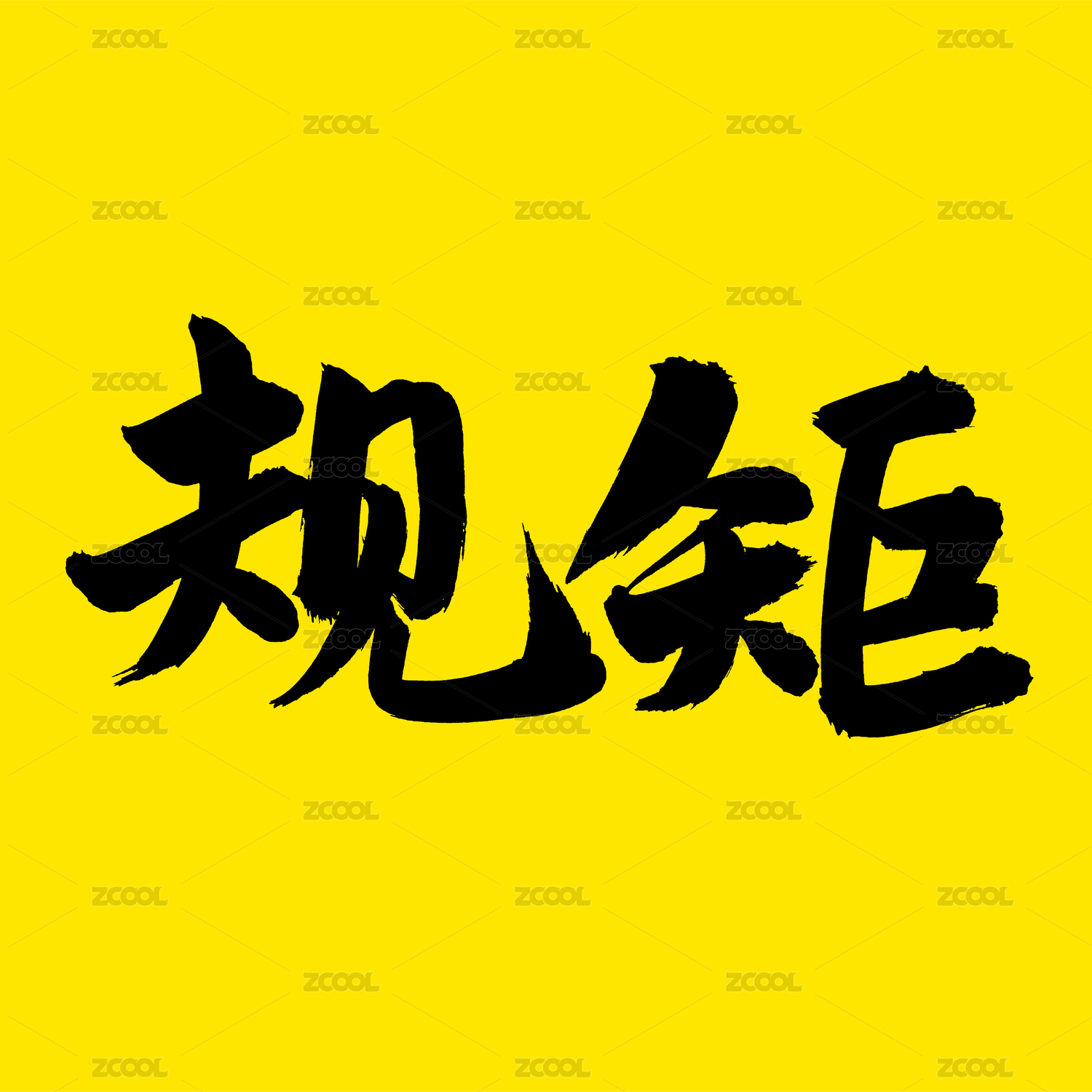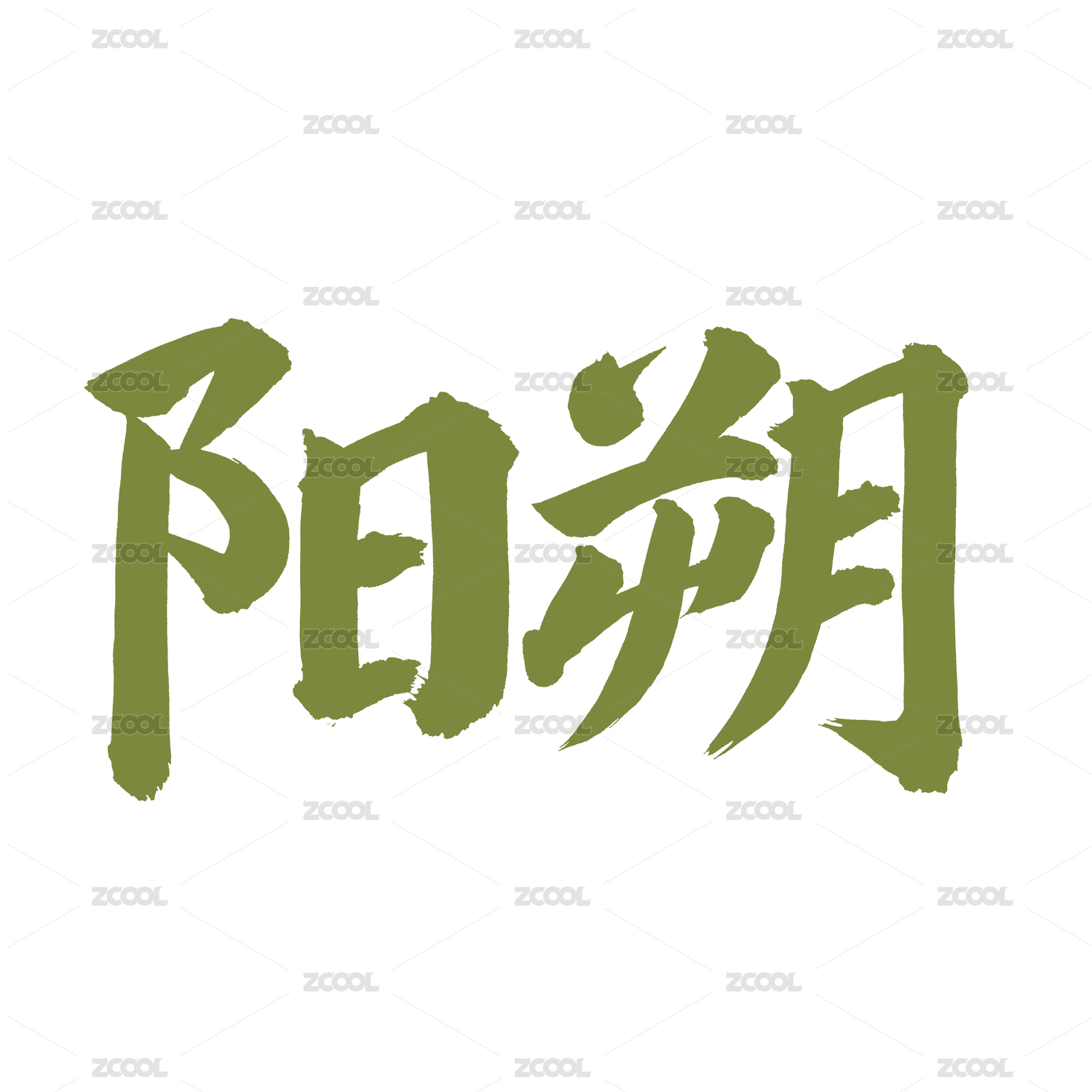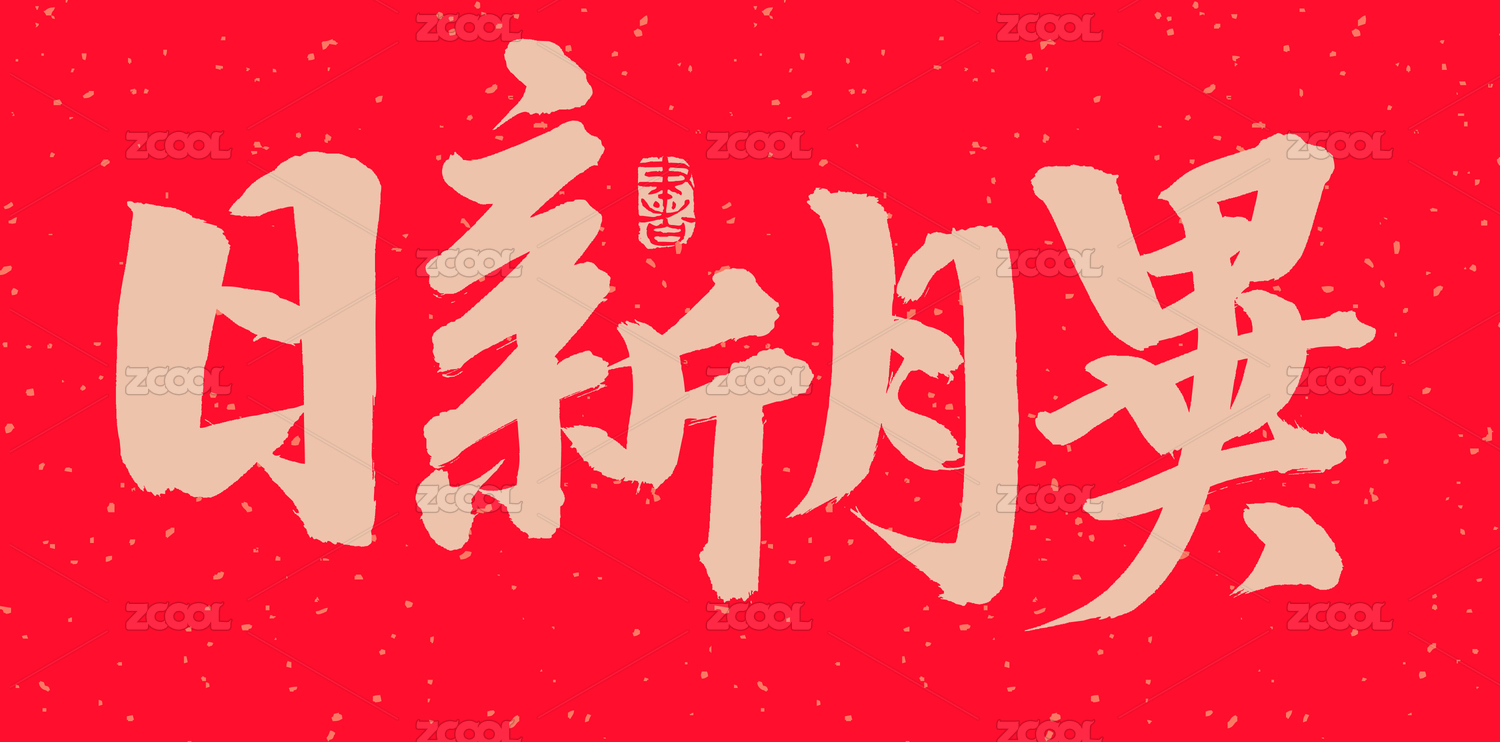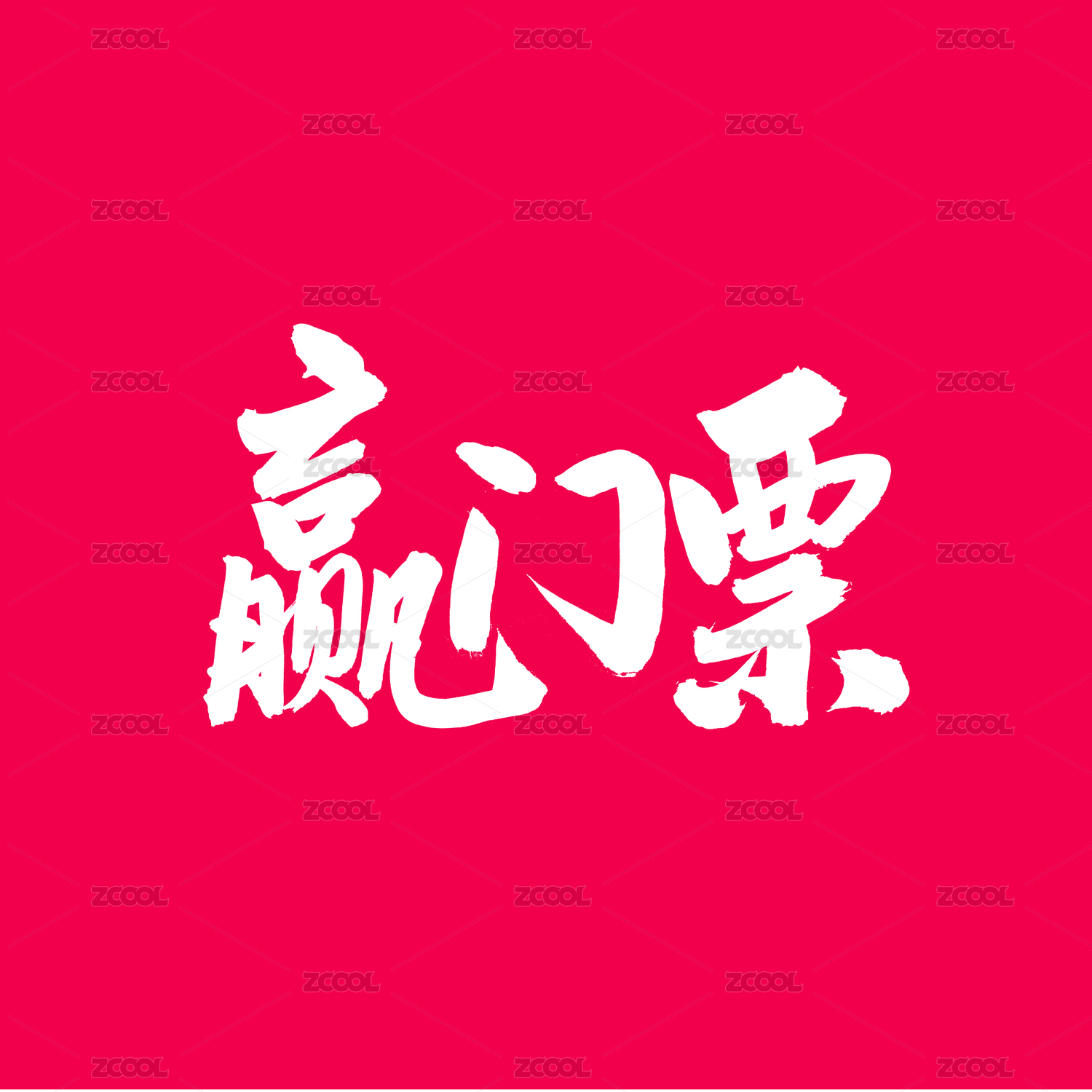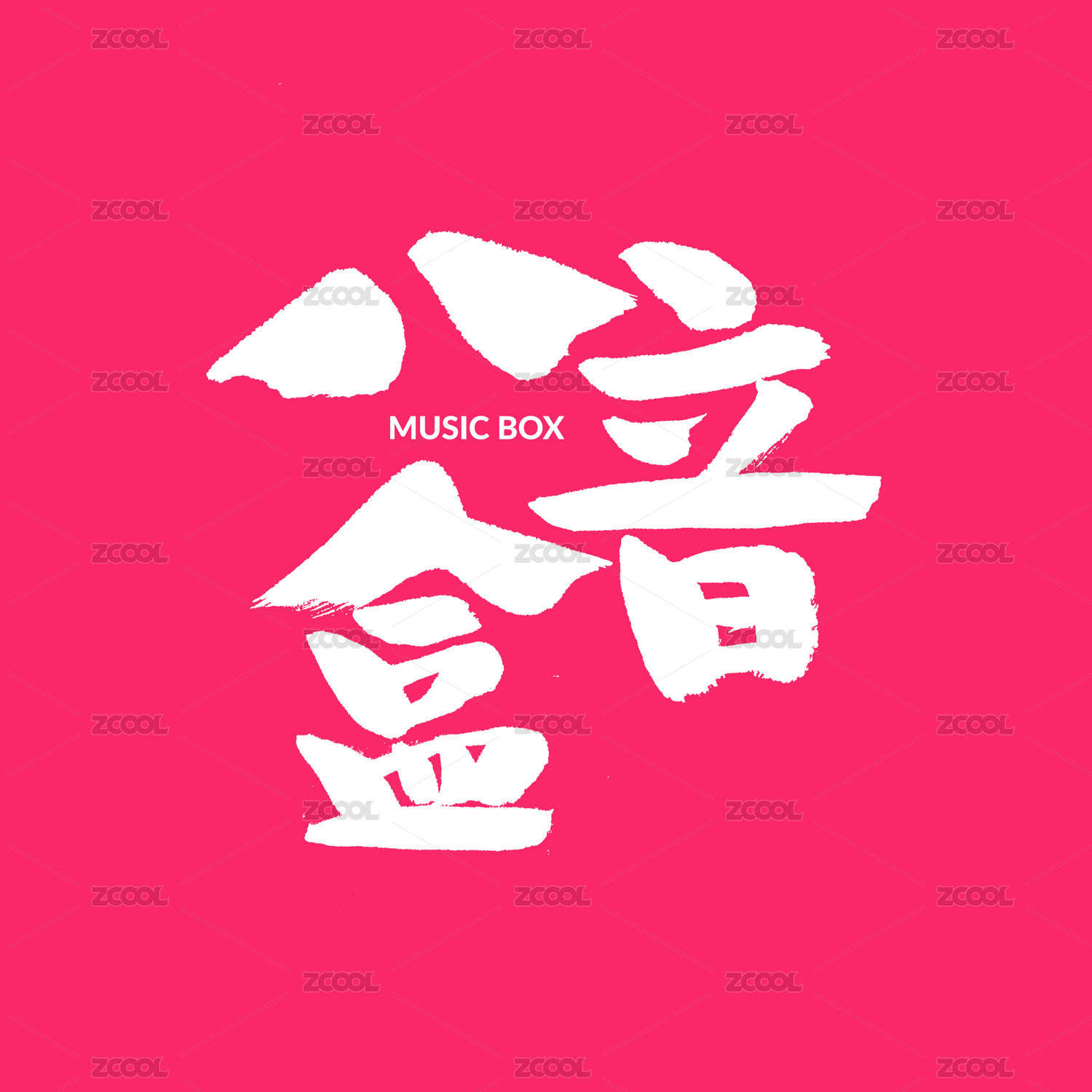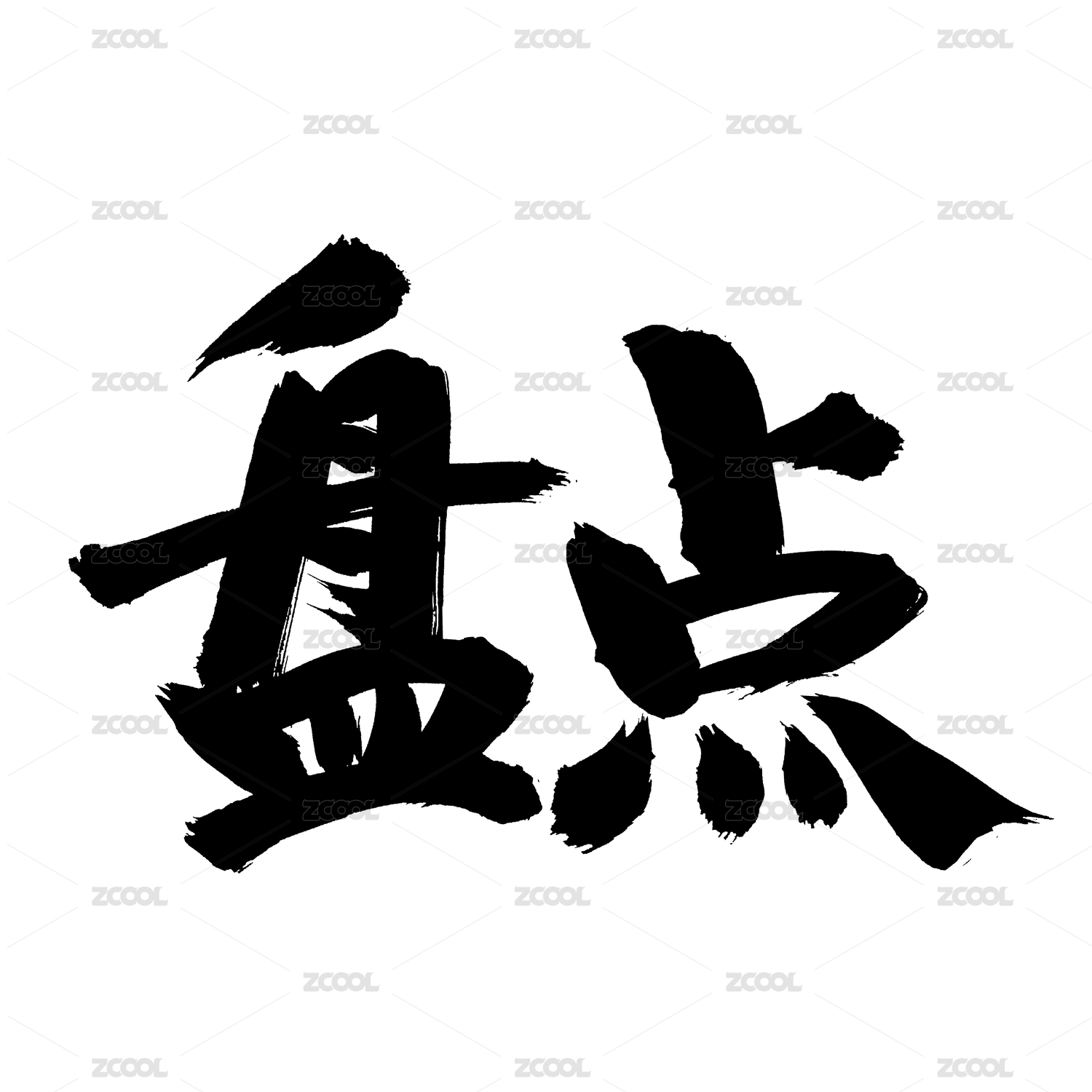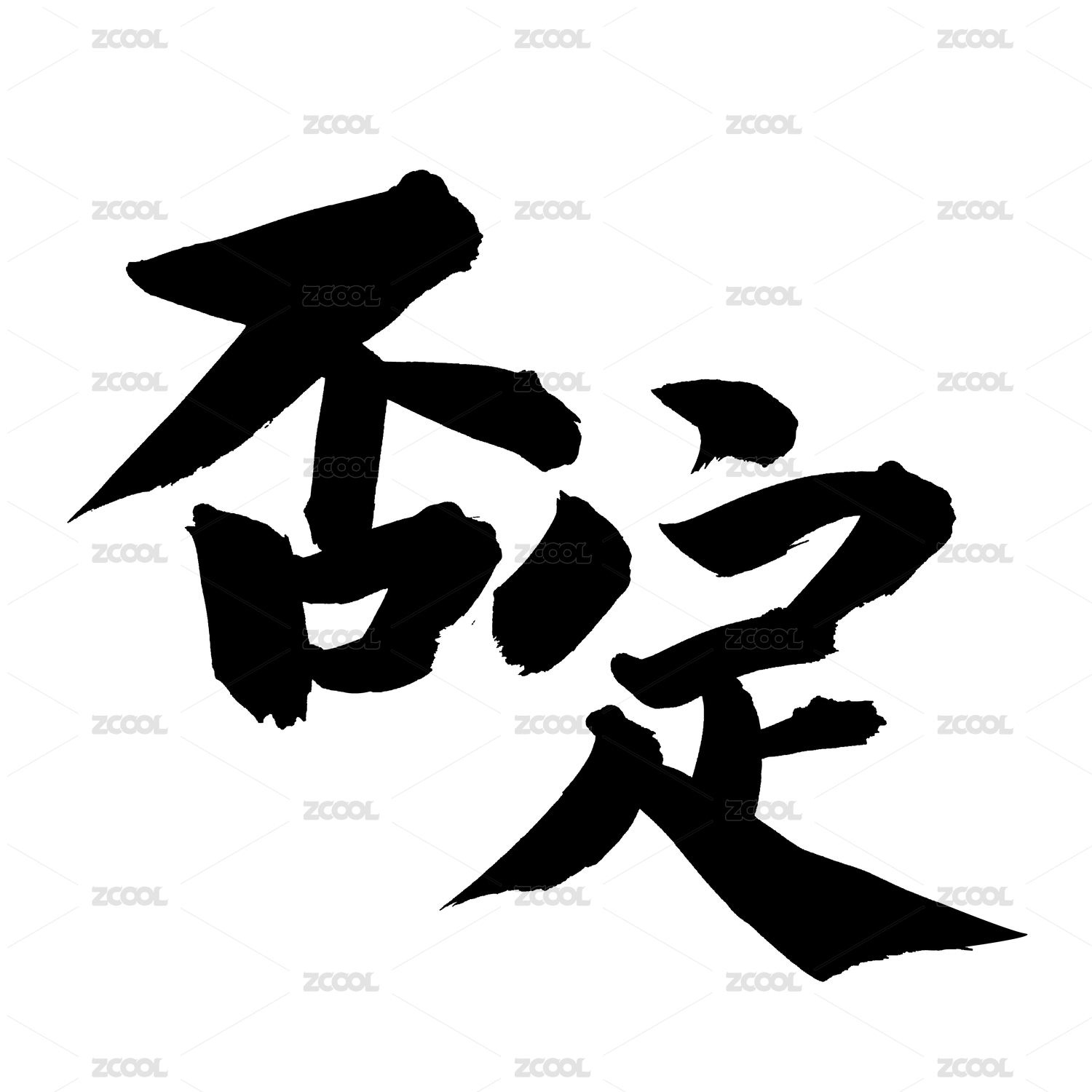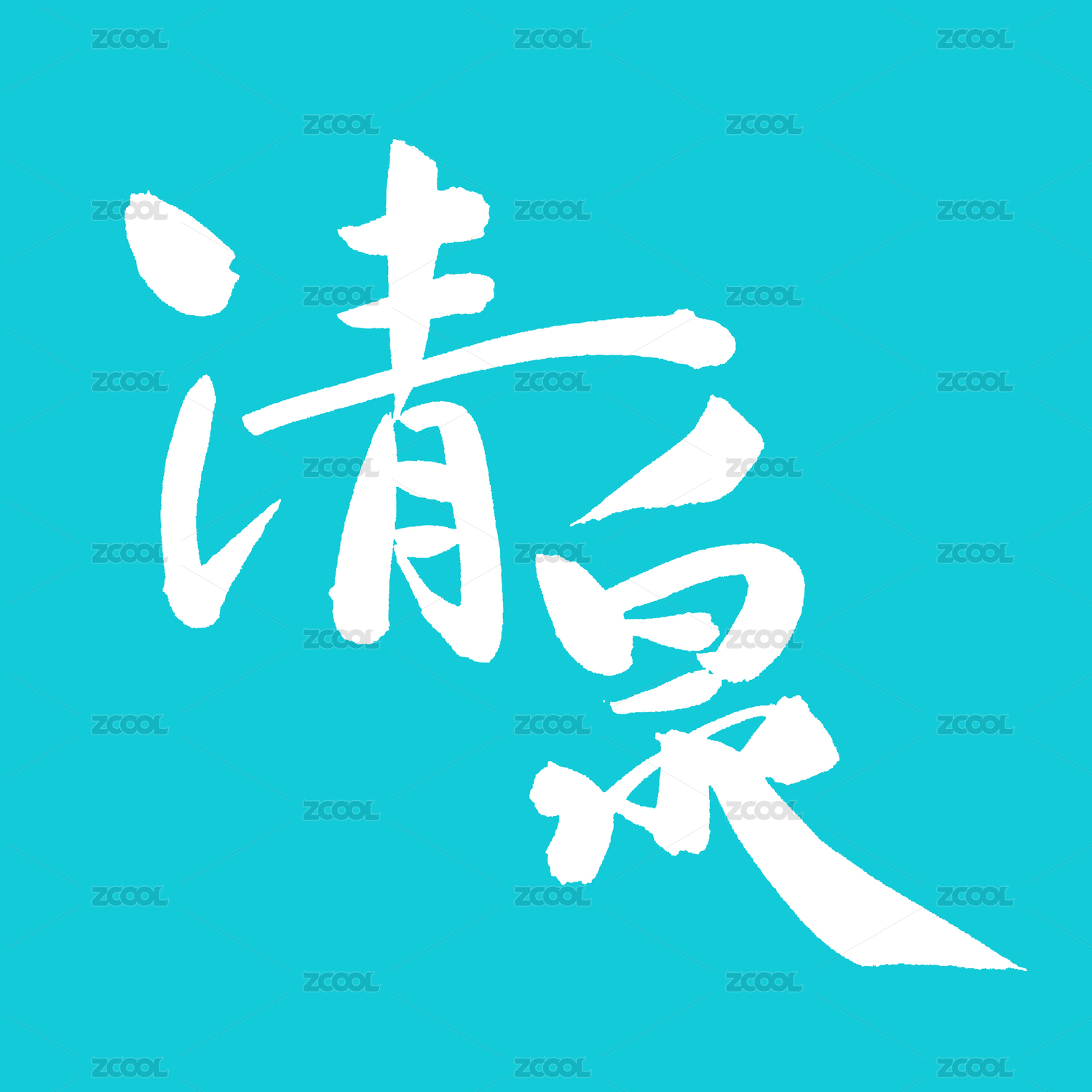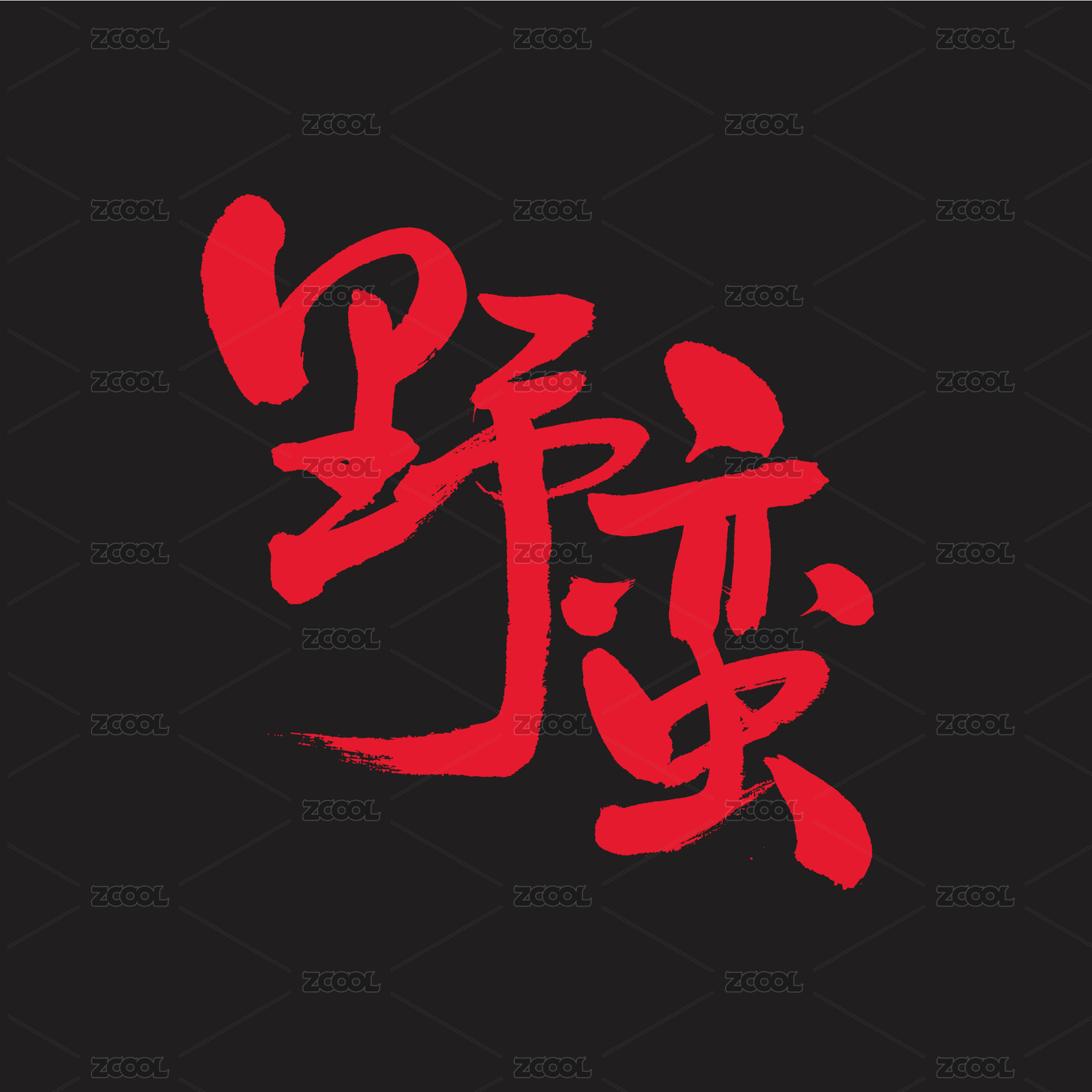
寒蝉手拙体
I 作者:siue<br>I 字体简介:寒蝉手拙体,主要精髓为发掘手写字体的手拙之美,字体给人一种逼真手写的视觉体验。虽应用范围有限,但有其不可替代和独特的价值。以创造的笔意和结构完成,形成风格独特的一套小众字体。<br>I 字数:本字体基于中华人民共和国GB2312-80字符集标准,采用TrueType和OpenType两种格式,共收容字形7586个。<br>I 使用范围:免费授权全社会使用(包括商用)。<br>I 版本信息:Version 1.000 2018年3月最新版。<br>文末附下载链接,最后感谢大家的使用。<br><br>